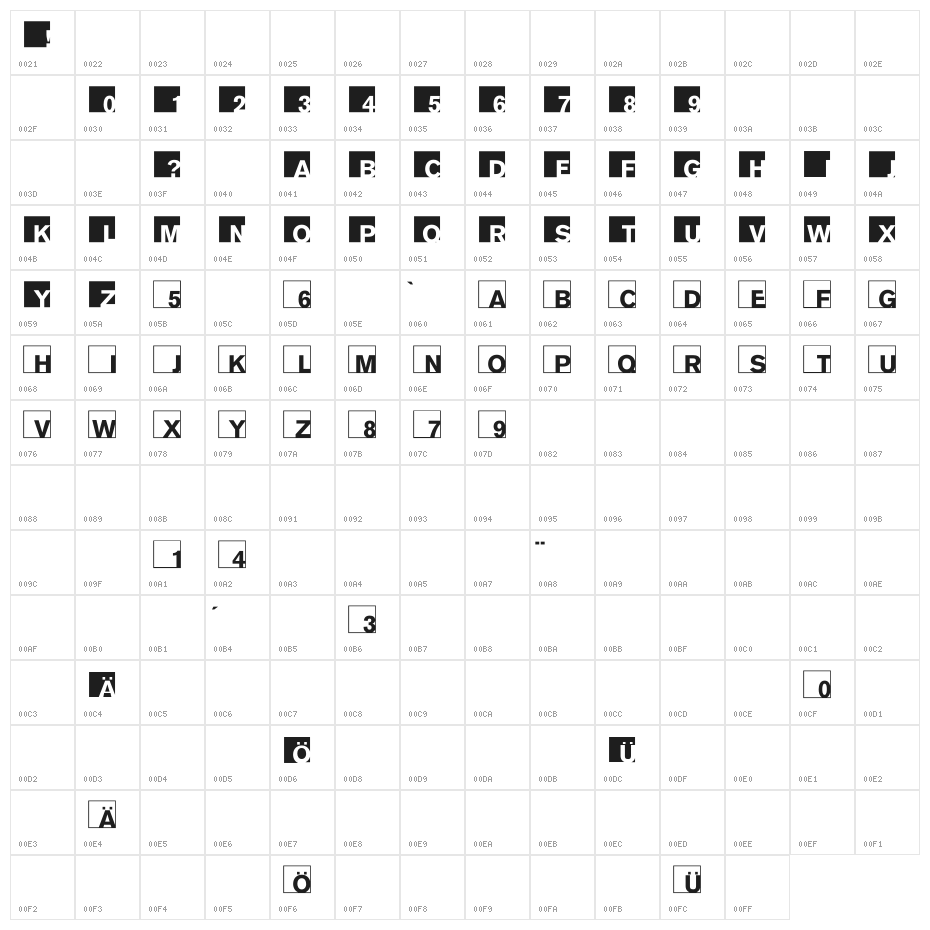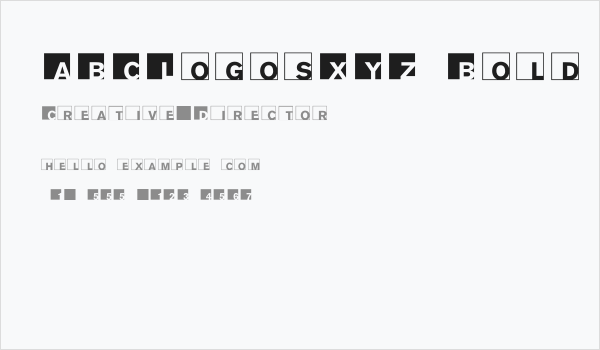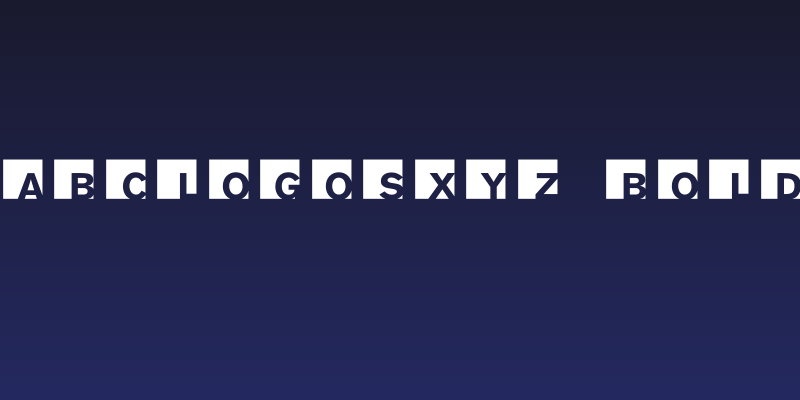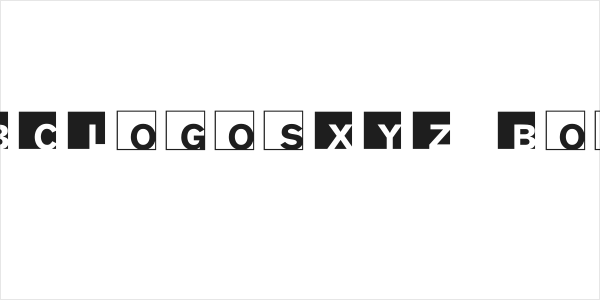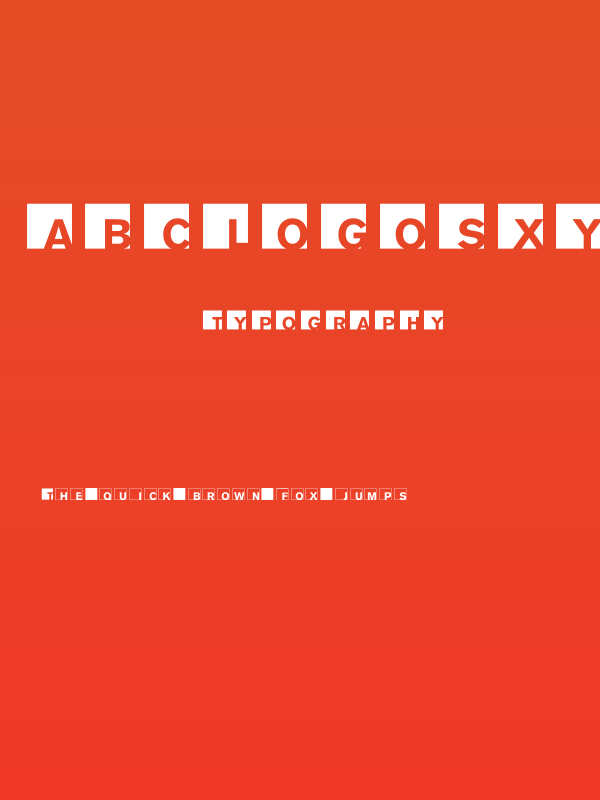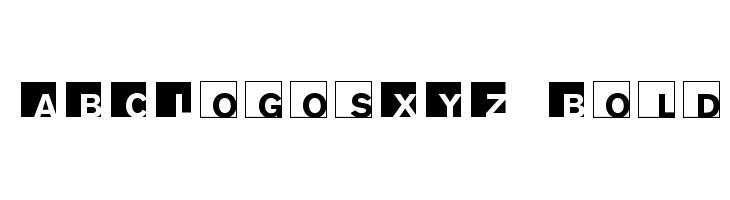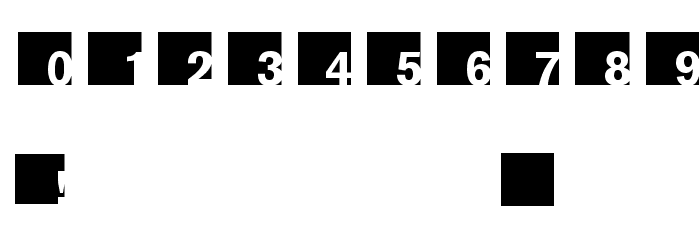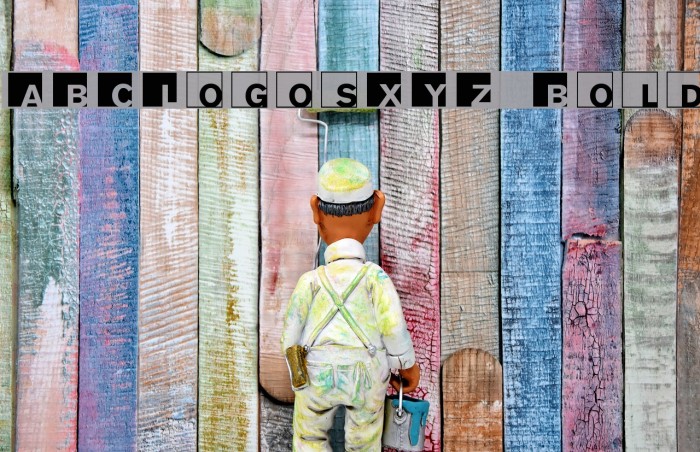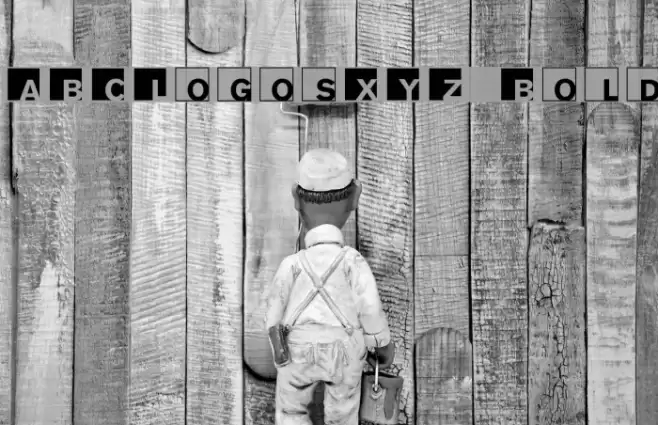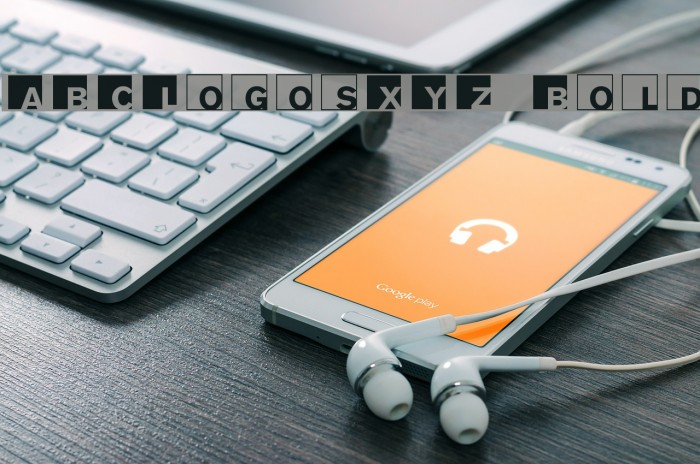
ABCLogosXYZ-Bold Font
✎ Decorative
| उपयोग का मामला | Logos, Headlines, Posters |
| सुझाए गए प्रोजेक्ट | Ideal for logos, branding, posters, and any design requiring a bold and modern aesthetic. |